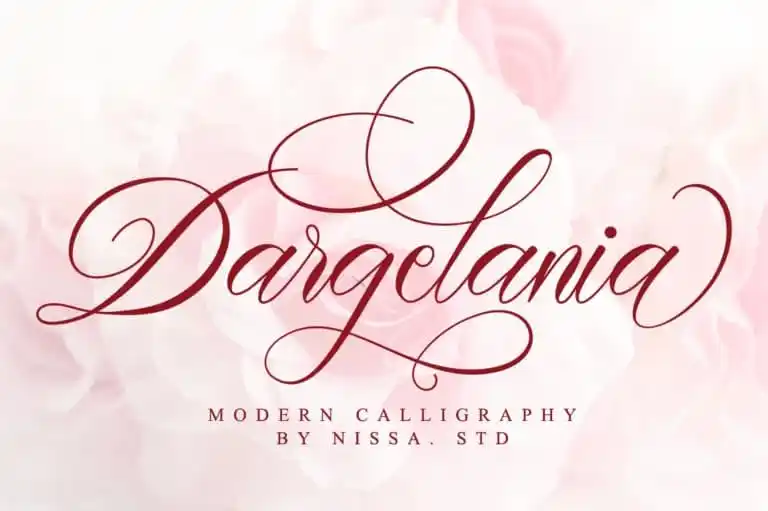
Dargelania – Calligraphy Font – Download Grátis
A Dargelania – Calligraphy Font é uma fonte ideal para quem busca personalidade e elegância em suas criações digitais. Especialmente adequada para projetos que valorizam a harmonia entre letras manuscritas e formas alternativas, esta fonte foi meticulosamente desenhada por 99designs. Ela combina um estilo elegantemente sofisticado com alternativas de caracteres únicas que permitem explorar infinitas possibilidades criativas. O que torna a Dargelania realmente única é sua PUA (Unicode Private Use Area) encoding, o que significa que você pode acessar todos os seus caracteres e swashes (formas alternativas) facilmente. Essa característica não só aumenta a funcionalidade da fonte, mas também permite uma ampliação de seu uso em projetos variados. A Dargelania destaca-se por sua versão de base baixada, linhas suaves e formas gerais que proporcionam um aspecto limpo e sofisticado. O conjunto de caracteres geralmente inclui diferentes graus de alternância, o que permite uma maior variedade nos projetos digitais, fazendo com que cada letra seja única. Para finalizar, a Dargelania possui opções de linha baixa variáveis, criando um design com linhas suaves e fluidas. Essa característica permite ajustes dinâmicos, permitindo que as letras se adaptem às diferentes fontes de texto sem perder sua identidade única. É uma excelente adição à sua coleção de fontes para projetos de artes gráficas que valorizam a criatividade e o estilo elegante.